2023 蒙纳春季字体沙龙回顾:再度启程,赋能未来
3 月 24 日, Monotype Meet 蒙纳春季字体沙龙(上海站)于汇亚大厦路演厅如期举行。这次久别重逢的线下交流机会,既承载过往包容开放的沙龙氛围,亦在春分时节呈现焕新的面貌。
本次活动邀请到厉致谦、刘育黎、陶帝三位字体领域的资深嘉宾进行主题分享。从历史人文、技术美学、未来趋势等多视角切入字体设计,同在场三十余位字体爱好者一起,探讨设计、创造、品牌的可能性。
2023 蒙纳春季字体沙龙现场
厉致谦:以设计为原点的多领域研究与实践者,TheType 作者,“上海活字”综合研究项目发起人,创新型字体公司三言联合创始人
隐字上海 & 上海活字
厉致谦老师以隐字上海为引入,带来了丰富的影像资料。手写招牌在街巷拆迁过程中浮现而出,它们书写于墙面、砖瓦、木板等多种材质上,呈现强烈的城市风格和时代温度。而其中所暗含的用字及书写变化,更是作为微观的“视觉遗迹”,映照出宏观历史变迁。
厉致谦
随后,厉致谦老师也继续深入,讲述了他发起的“上海活字”综合研究项目及其背后第一代中文字体设计师的故事。跨越多个年代的人员组成,泛黄卷页的珍贵手稿,初代黑体的逐渐成形……中文字体设计的记忆尽数呈现。
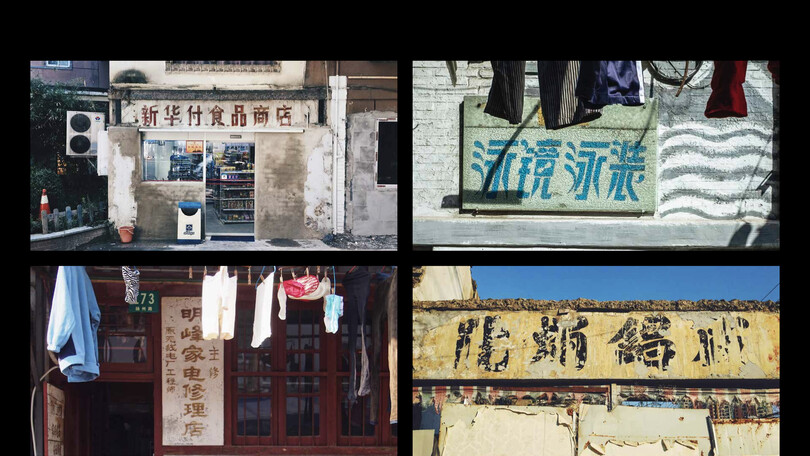
隐字上海
从厉老师沉静有力的分享中可以感受到,字体并非静态的、沉默的,而是关乎个体与周遭,激发我们从过往的记忆和叙述里汲取生生不息的创造力。
刘育黎:设计工作室锚坞联合创始人,长期从事字体设计教育和写作,关注字体和流行文化的结合点,动画、像素和文鸟爱好者
中文字体技术漫谈
刘育黎老师则以我们习以为常的打字输入操作为线索,切入字体开发设计,带领大家了解中文字体背后更多的技术美学。
刘育黎
汉字依托于国标码的推出,有了相对应的机器语言,并通过输入法进行逻辑转换和字符对应;与此同时,编码的不断完善与输入法的更新迭代,使得输入汉字变得更为简捷高效。
而决定屏幕效果的,则是字形设计和渲染技术。随着电子载体在分辨率和色彩上的升级,如棋盘般排布的点阵字体,逐渐转向由数学曲线描述的矢量字体。配合渲染技术,汉字呈现出更清晰柔和的边缘,以及更大的设计可塑性。
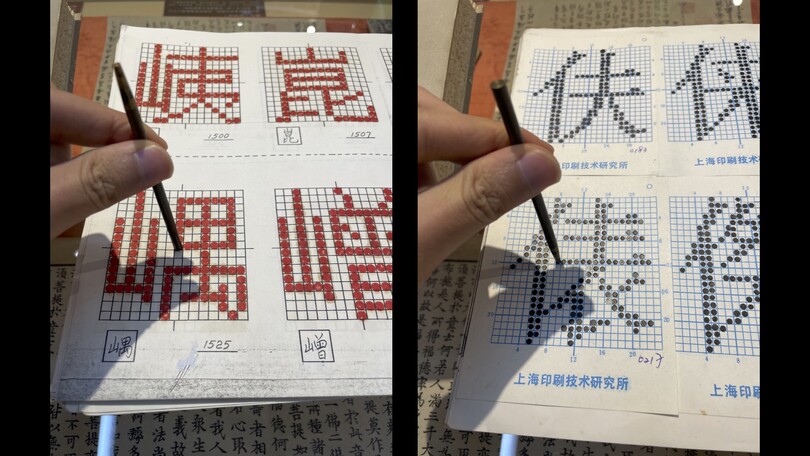
点阵字体
最后,刘育黎老师也指出,回望中文字体技术的发展历程,既帮助我们理解过往,也指向未来。如何与技术发展相结合,深度理解用户需求,激发出中文字体更多的可能性,将是字体设计者和开发者们需要持续思考的问题。
陶帝:蒙纳字体设计师,国际字体协会(ATypI)成员,深圳市平面设计协会会员
AI 趋势与字体设计
围绕 AI 应用的讨论热度逐渐蔓延至字体设计领域,关于强 AI 时代的来临将对字体设计产生何种程度的挑战,还存在诸多争议。陶帝老师以此为引入,从机器学习模型谈起,进而阐述字体设计的微妙之处。
陶帝
陶帝老师首先展示了他通过 Midjourney 生成的案例。与清晰逼真的人像图片相比,包含字体的图片则在细节上经不起推敲。由于当前字体所能提供的训练量远低于文字、绘画及摄影,AI 程序对字体的描摹只能触及模糊的视觉形态,尚不具备生成整套可识别字体的能力。
紧接着,陶帝老师继续围绕字体设计,深度分享了多个趣味内容,如以 AI 图像呈现多款经典字体的迥异风格,翔鹤黑体蕴含的灵动匠心,视觉字号的概念及应用等等。这些话题虽角度各异,却指向了共同的核心,即字体并非单纯的信息符号载体,而是包含更为微妙的情绪和共鸣。
因此,身为字体的使用者或设计者,面对快速迭代的 AI 浮现危机感的同时,也值得再次审视反思过去习以为常的问题:我们是谁,我们用字体表达什么,如何表达得更好。这将会是我们处理与 AI 的关系,以及身处更多技术变化中,需要明确的核心立场。
陶帝与字体爱好者在会后继续交流
结语
本次活动亦最大限度地给予在场字体爱好者们讨论空间。除去每轮分享后的即时答疑环节,茶歇时间和活动结束后,都能看到大家自发地与嘉宾继续交流。
蒙纳春季字体沙龙于上海开启的第一站,至此圆满结束,既是久别重逢,也是新的序章。未来,Monotype Meet 还将呈现更丰富的形式与更多元的视角,期待我们在下一站继续相见,共飨字体之美。